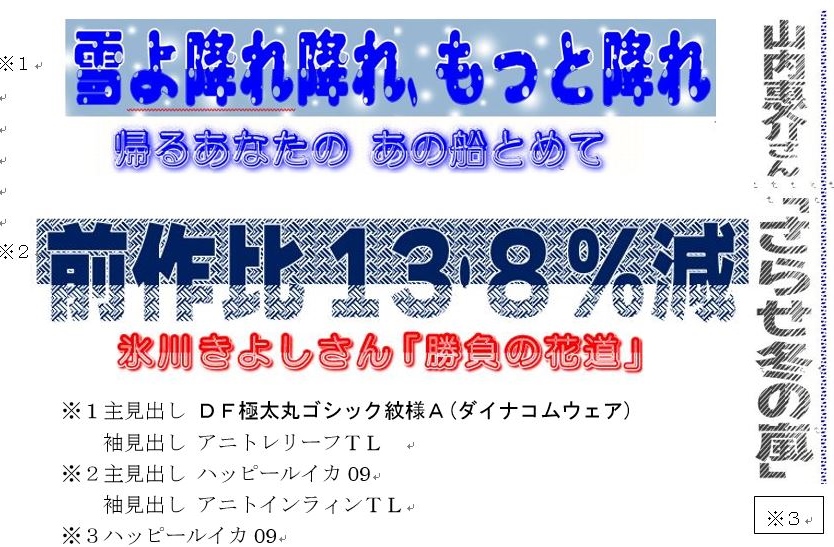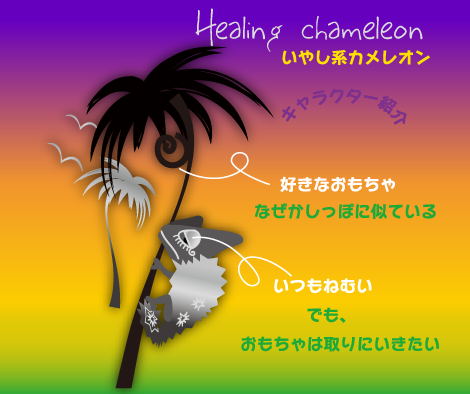
タイプラボの等幅フォントが気に入って、ニタラゴルイカとかアトニを愛用していました。
そういう検索に引っかからない対処法はあったと思いますので、手が空いている時にやってみようと思います。
さとうゆたか  2021年10月27日(水) 10:55 [修正]
いちおう対処してみました。
該当ページの<head> タグ内に
<meta name="robots" content="noindex,nofollow,noarchive" />
と入れてみました。
相変わらず検索結果には出てしまいますが、検索システム内のキャッシュを削除するのは、少し手間が掛かります…。
時間が空いた時に、できたらやってみますが…。
メルマガの文字化け  たま  2018年9月1日(土) 21:15
Windows10のGmailでメルマガを受信しているのですが、ほぼ毎回文字化けしている箇所があります。
これはいわゆる「波ダッシュ・全角チルダ問題」で起きているのだと思います。
見た目は同じなのにMac系とWindows系で「〜」の内部コードが違うという問題です。
https://ja.wikipedia.org/wiki/Unicode#%E6%B3%A2%E3%83%80%E3%83%83%E3%82%B7%E3%83%A5%E3%83%BB%E5%85%A8%E8%A7%92%E3%83%81%E3%83%AB%E3%83%80%E5%95%8F%E9%A1%8C
このあたりは文章の作成・受け渡し方法やメルマガのシステムなどが絡んでくると思うので解決は難しいのかもしれませんが
フォント系のメルマガで文字化けしているというのはなんだか美しくない気がするので
もし対応できるようなら対応してくれると嬉しいです。
さとうゆたか  2018年9月1日(土) 22:10 [修正]
たまさん、ご報告ありがとうございます。
全角の「〜」が、化けているようですね…。
同様に文字化けしているという方が多いのでしたら、メルマガ原稿を作るときに「〜」を使わないようにするしかないでしょうかね…。
同様に文字化けしている方、報告していただけると幸いです。
同じ文字化けを見つけました。  匿名  2021年8月1日(日) 15:47 [修正]
同じくWindows10で受信しているのですが、画像の部分の、
さとうゆたか  2021年8月1日(日) 16:20 [修正]
匿名さん、ご指摘ありがとうございます。
自分でタイプするときは注意してるんですが…。
他のサイトからコピペしたとき、チェックを忘れてしまいました。
正しくは「70〜80年代に流行」ですね。
以後、気をつけます…。
ニタラゴルイカ無料版の濁点について。  匿名希望  2020年11月27日(金) 16:11  Mail
こんにちは。ニタラゴルイカの無料試用版の使用者です。
ちょっと聞きたかったのですが、濁点半濁点って、搭載されている濁点半濁点以外で濁音半濁音を作っていいのでしょうか?(例:Wordの図形など)
ちょっと気になったので、聞いてみます。
さとうゆたか  2020年11月27日(金) 16:18 [修正]
新たなフォントファイルを作るわけでなく、アプリ内で工夫して濁音・半濁音の文字を作るのは構いませんよ。
商品版を購入したほうが、ずっと便利だと思いますけど…ね。
えれがんとフォント試用  つね  2019年11月2日(土) 13:52  Mail
知合いの店で開催されるイベントを支援してチケットを制作するため、店名に似た書体を探したところ「えれがんと」とわかり、無料ダウンロードを申込み、当面は間に合いましたが、つぎの2点がよくわからないままになっていますので、チェックするポイントをご指導ください。環境は Windows 10 です。
1.返信いただいたメールの本文が記号や英字に化けて読めなかったが、URL とわかる行を引用して、ダウンロードすることは出来ました。
2.「えれがんと」を適用すると濁点が付く文字が出なかった(空白になる)ので、幸いに今回は濁点なしで間に合ったが、今後の応用が出来るか迷っています。
さとうゆたか  2019年11月2日(土) 14:00 [修正]
無料のタイプラボフォントは「お試し用のフォント」です。
濁音半濁音や教育漢字以外の漢字は含まれていません。
そこのところ、よろしくお願いいたします。
えれがんとフォント試用  つね  2019年11月3日(日) 6:56  Mail [修正]
了解しました、ありがとうございます。
ちょっと気になって  匿名さん  2019年4月23日(火) 13:35
初めて投稿いたします。
最近booth様でさとう氏の製作なされたフォント「ニタラゴルイカ」を購入させていただきました。
早速堪能しているのですが、規約面で少し気になったことが…
フォントの利用について、webブラウザ内スタイルシートによるフォントの変更で
ブラウザ用のフォントを始め、HTML5ベースのオンラインブラウザゲームをプレイすることは大丈夫でしょうか?
氏が販売なされている組み込み用ライセンスの規約に反してるのではと思ってしまって…
さとうゆたか  2019年4月23日(火) 14:05 [修正]
フォントを購入された方が、ご自分の環境内のwebブラウザに表示するのは、問題ないと思います。
そういうご質問ですよね?
匿名さん  2019年4月23日(火) 19:02 [修正]
素早い御回答感謝いたします。そして返信が遅れて申し訳ございません。
質問の件、その通りです。
使用に関しては問題ないとのことで安心、スッキリいたしました^_^
ニタラゴルイカやNTLG系統のフォントは色々な場所で目にしてすごく惹かれるフォントで前々から興味がありました。
ブラウジングだけでなくさまざまなシーンでこれからも使っていきたいと思います。ありがとうございましたm(_ _)m
メルマガで私のフリーフォントを紹介してもらえないでしょうか?  初州  2018年9月14日(金) 22:21  HP
初めまして.初州と申します.
要件は,メルマガで私の自作のフォントをご紹介いただけないでしょうかというご相談です.
フォントの名前はTabashikeというのですが,添付の画像のような,不思議な形をしたフォントです.(画像では上からひらがなで「ゆうらくちょう」「かすみがせき」「えどかわばし」「いけぶくろ」です)
私は今このTabashikeを配布する計画を立てております.現状,作者の私だけが使用しているわけですが,それよりも配布して多くの人の目に触れるほうが,このフォントの使命がより確かに果たされると思うからです.
Tabashikeの使命というのは,「ディスレクシア」という一種の発達障害への認知を向上することです.より詳しいデザインの背景や狙いなどをウェブサイトに書きました.
ご感想ありがとうございます  takumi  2018年5月7日(月) 6:20  HP [修正]
yukoさん、はじめまして。執筆者のtakumiです。
ご感想ありがとうございます。
フォントというものがそもそも誰かの手によって作られた成果物であることを認識している人自体が少ないような気がしています。
僕もリアルでフォントの話をした時に、「え?フォントって『あいうえお』を作れば『かきくけこ』が自動的にできるようなものじゃないの?」と真顔で言われたこともあります(笑)。
たぶん、これはフォントに限った話でもなく、どういう創作物の恩恵を受けている人達にもそういう認識でいる人が一定数いるのでしょう。
作者への敬意を持ってもらうためには、そもそもその成果物が、誰かの手によって時間をかけて作られている、ということを認識してもらうことから始める必要があるのかもしれません。
これからも興味を持ってもらえるような記事を書いていけるよう努めてまいりますので、よろしくお願いいたします。